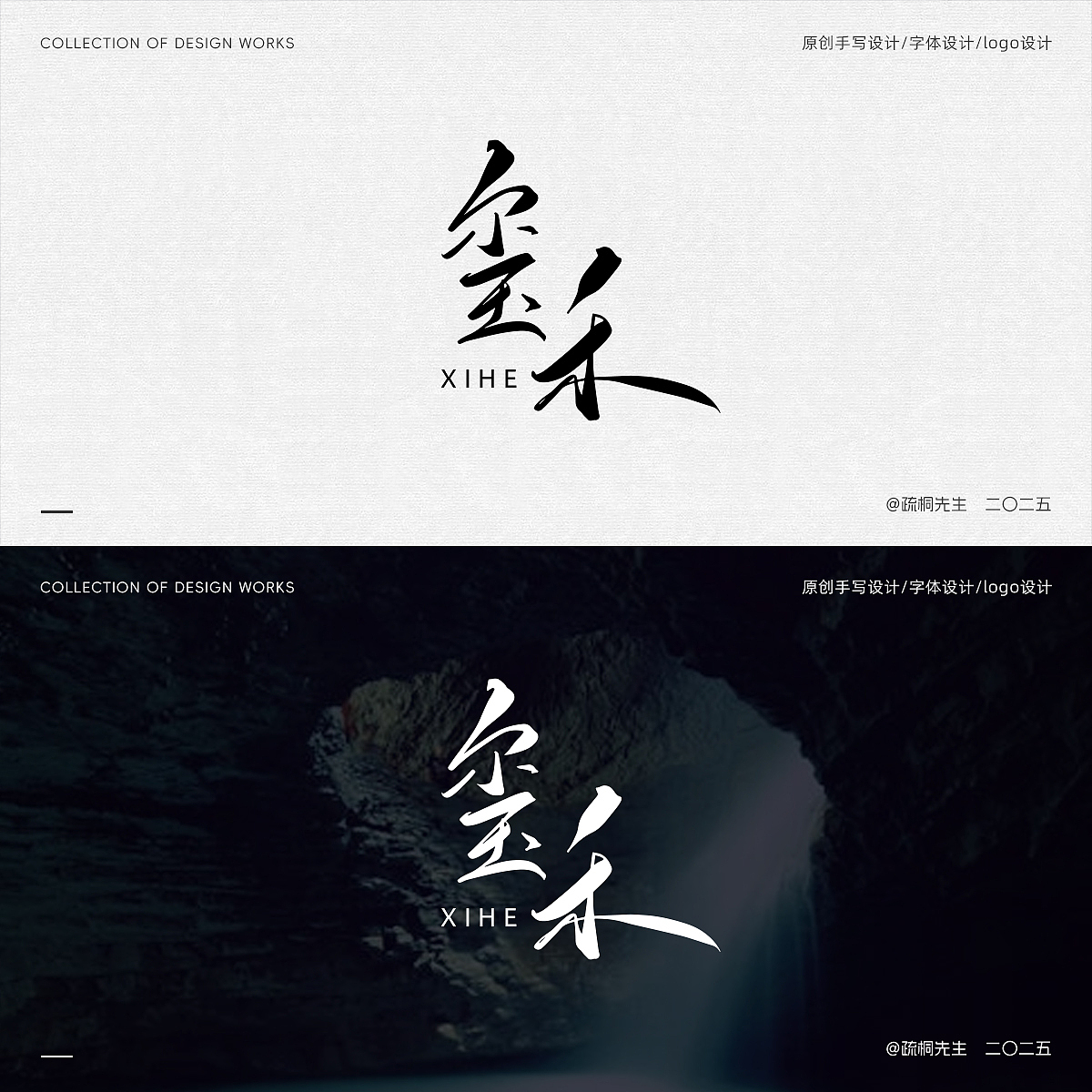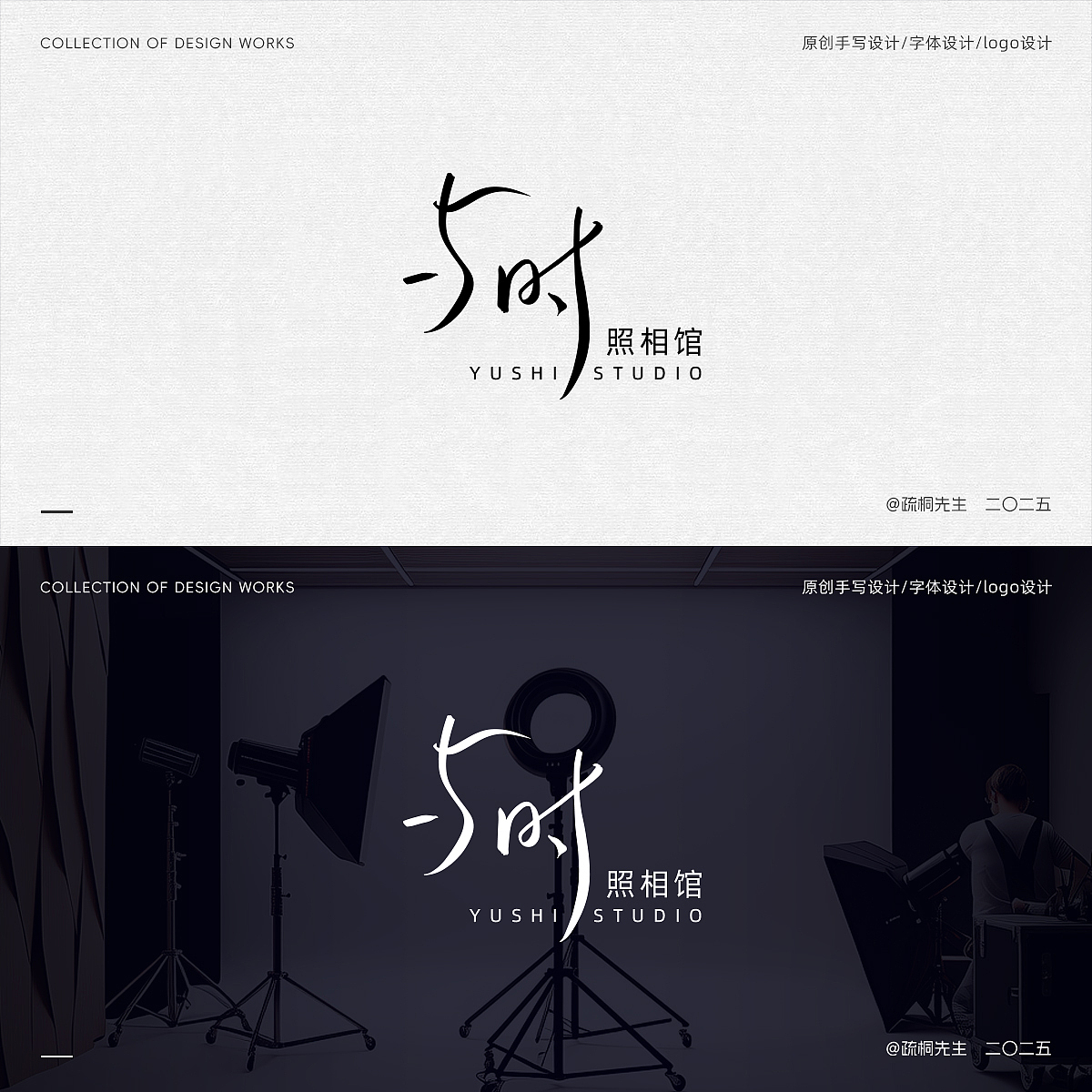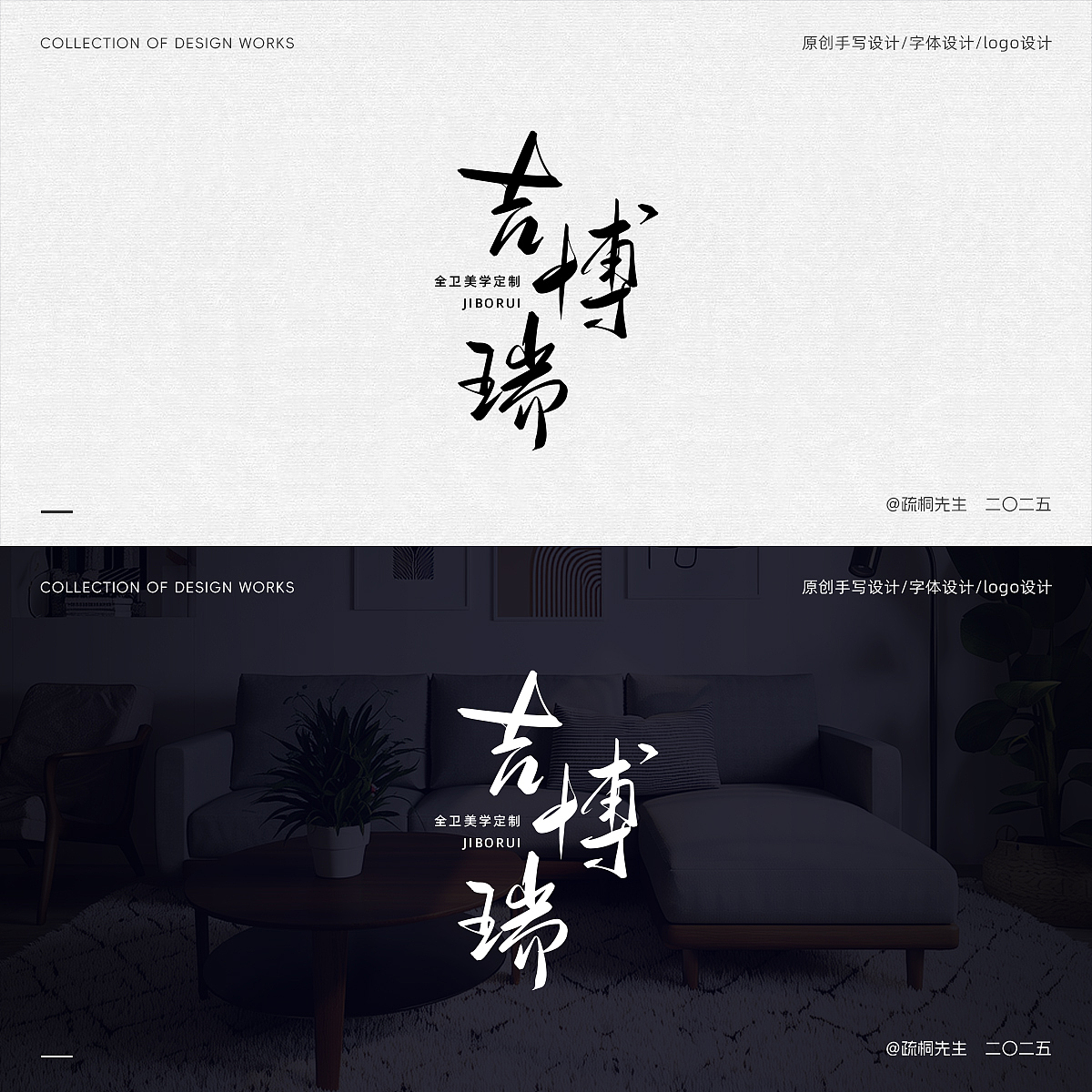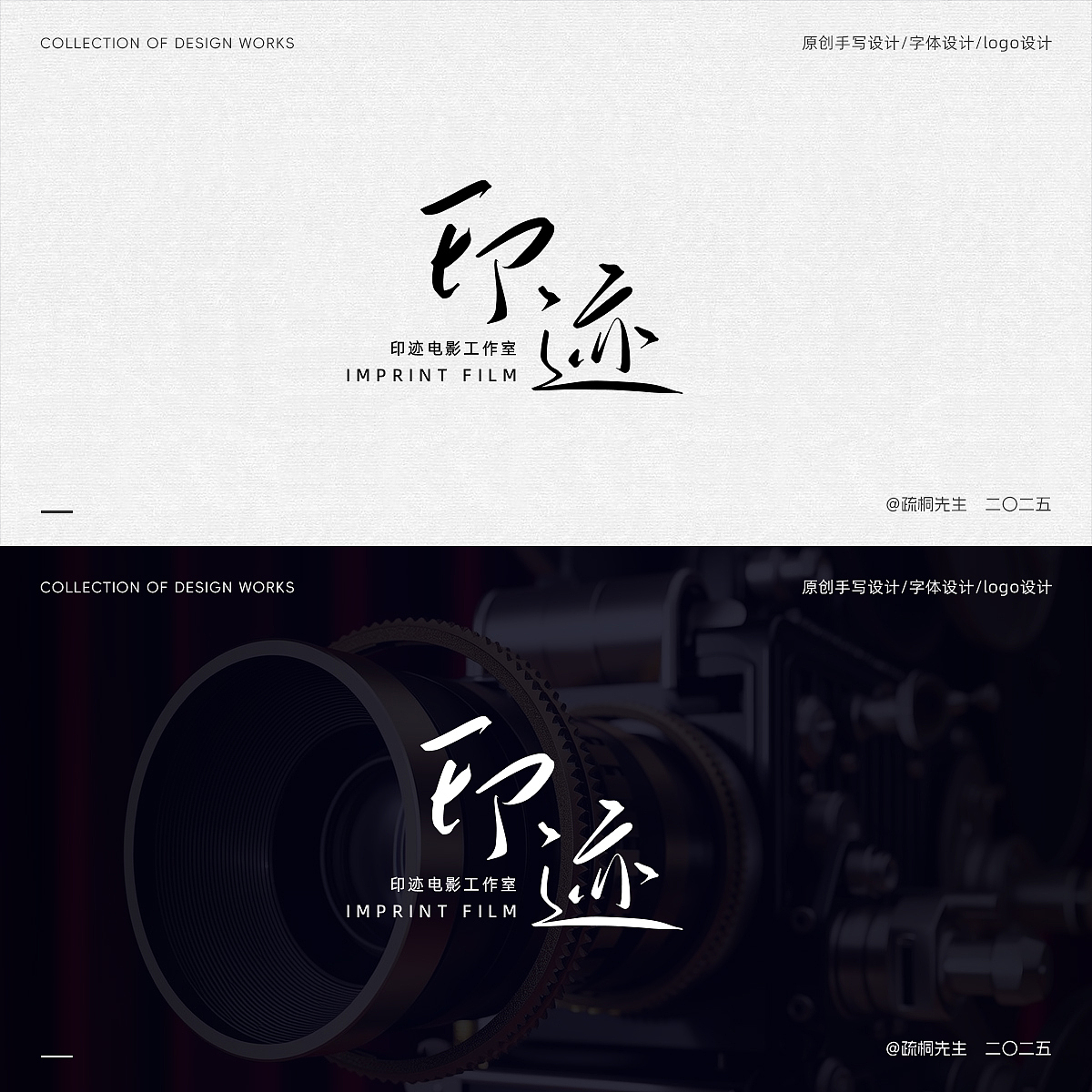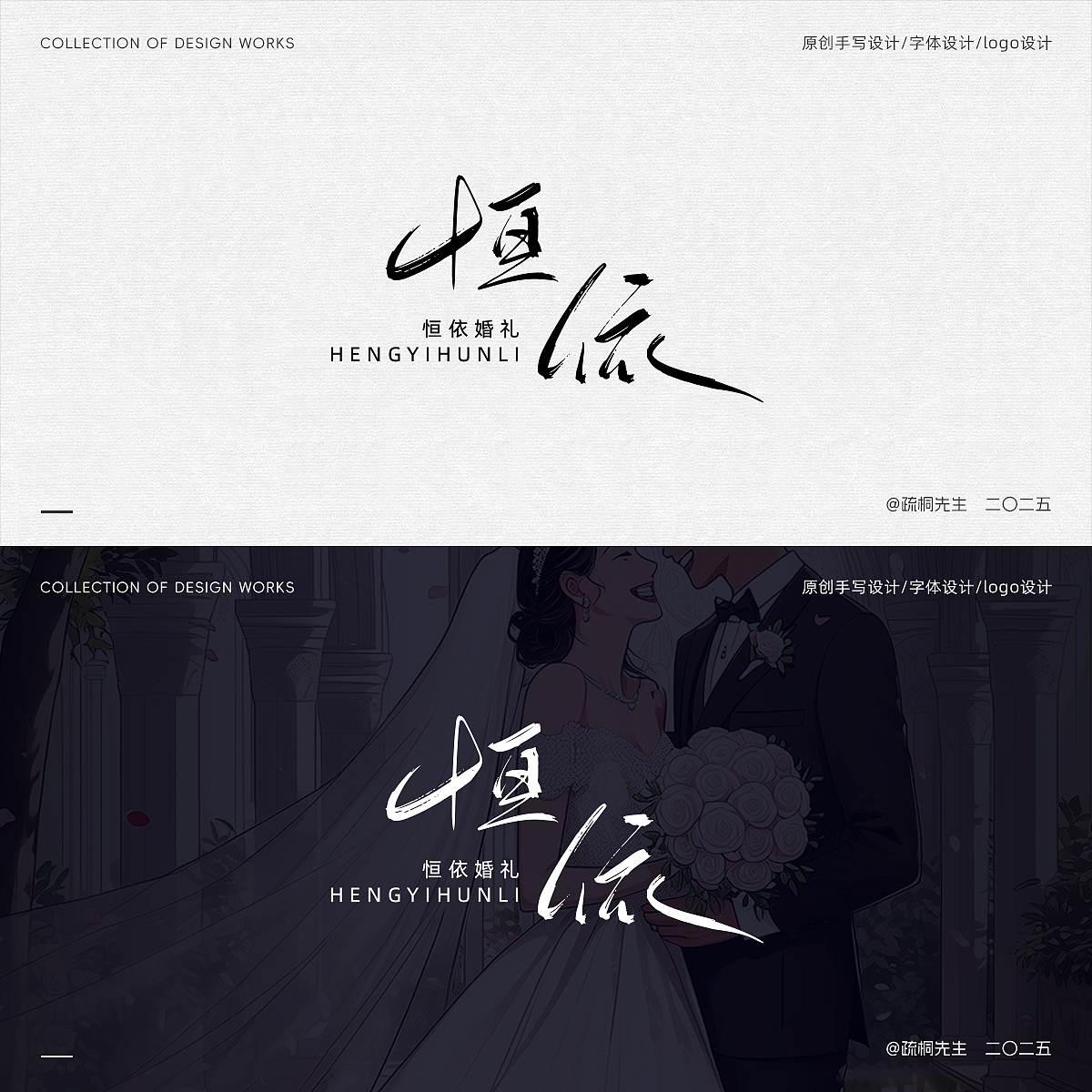
第七期 手写字 书法字体设计 字体logo 文字水印logo
汉字的魅力是无限的,字体设计是有很多种表现形式的。最近写的工作室,摄影和婚礼婚纱还有服装,美学相关的字体和logo比较多一些,当然还有一些宣传口号和广告语,还有一些影视作品,比如说短剧名称,电视剧电影名称,海报或者封面名称等等。有人问单纯的字体可以不可以当成logo来注册,这个答案是肯定的,就像人民日报,解放,红旗,全聚德,胡庆余堂等等,这些都是用纯手写字体来当成一个企业的标志logo来用的,所以单纯的手写体当然可以当成独一无二的logo来用啦!后面会持续更新,有喜欢这方面设计的朋友们,欢迎大家互相交流!